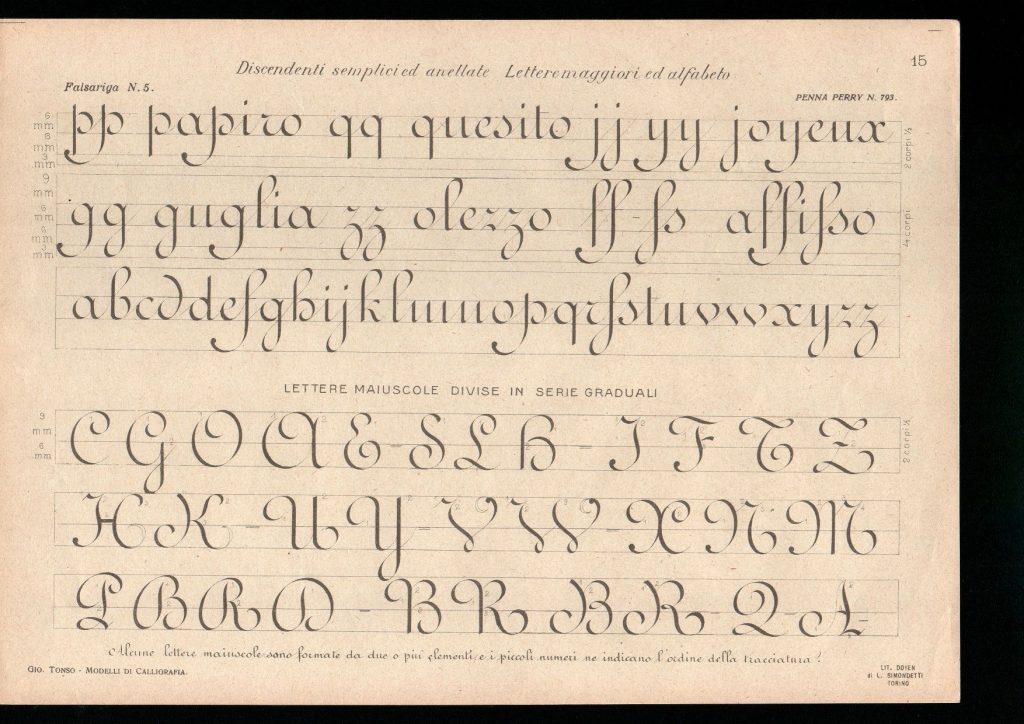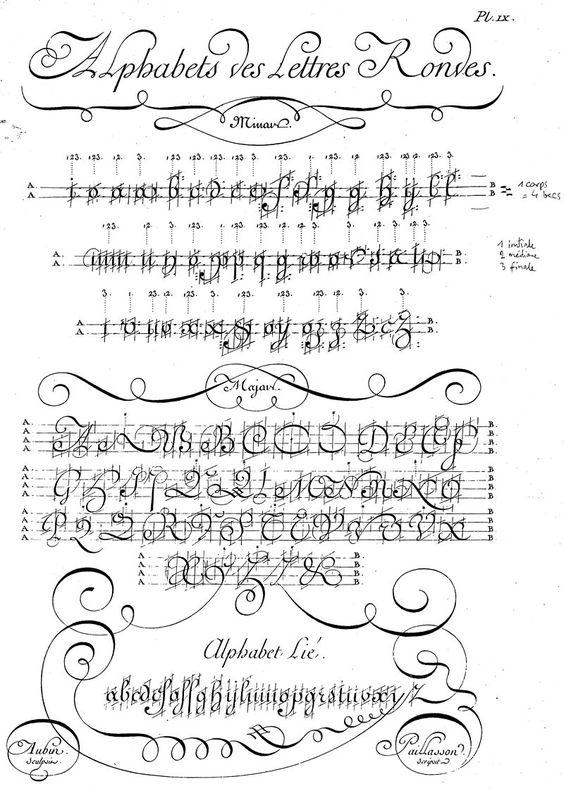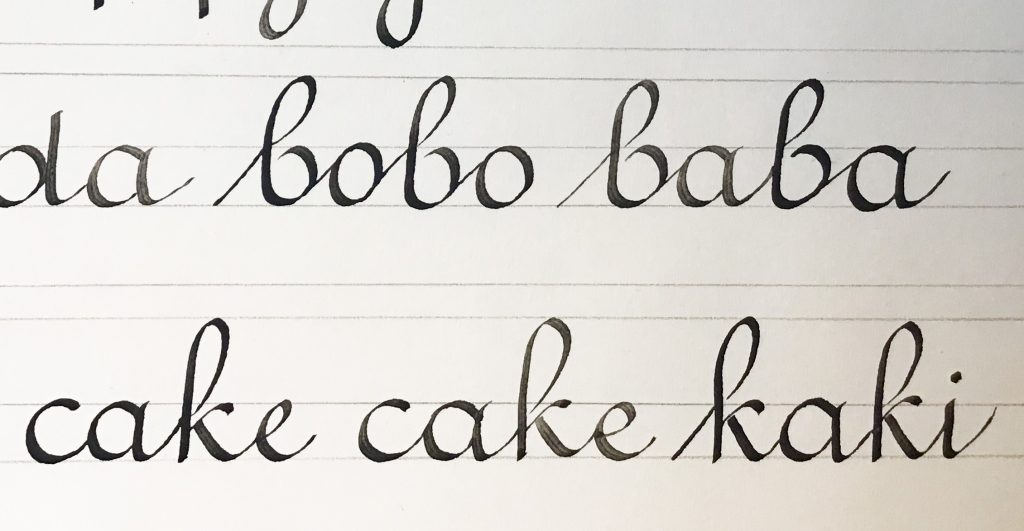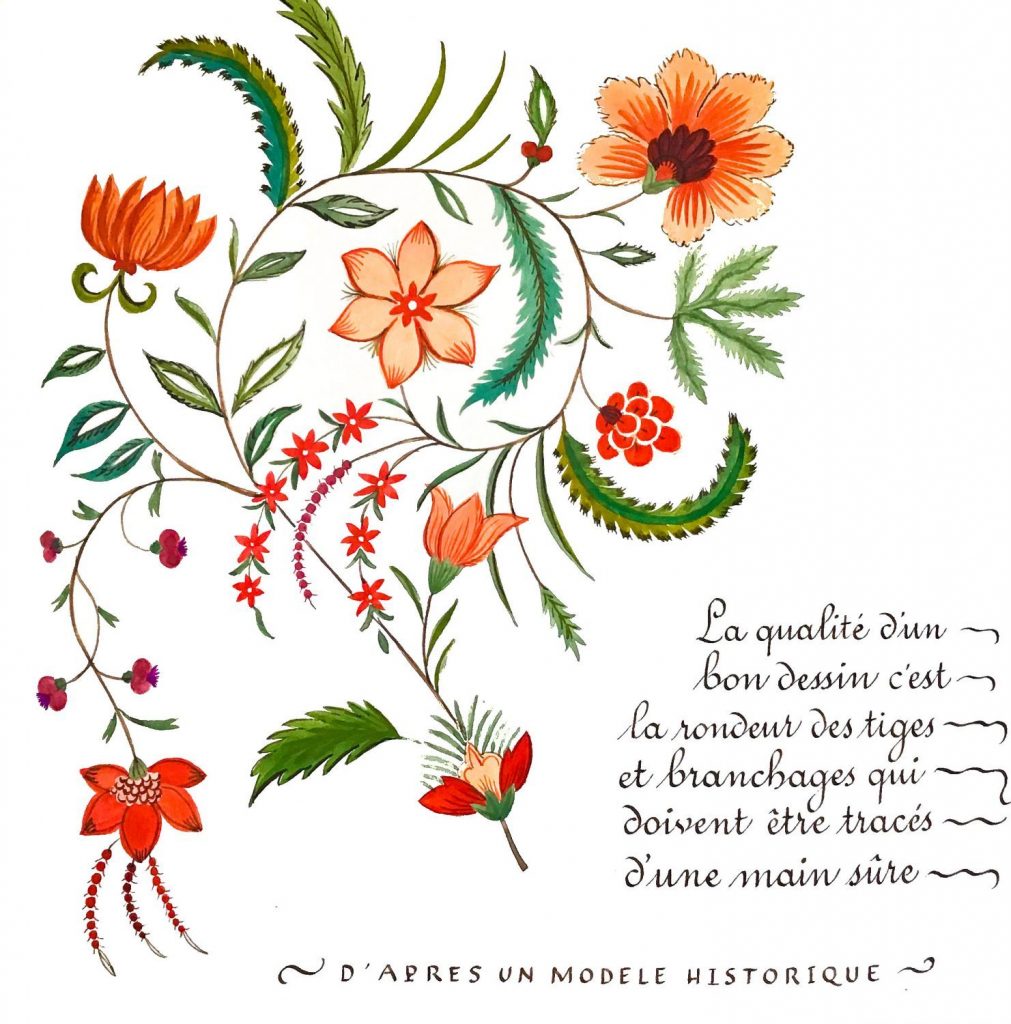
Ces dernières semaines j’ai été propulsée dans le XVIIIème siècle : cela a commencé avec un magnifique cours en ligne sur Skillshare sur la réalisation des motifs des Toiles de Jouy. J’ai profité de cet engouement soudain pour les cotons imprimés du XVIII pour aller visiter le très beau musée de la Toile de Jouy (à Jouy-en-Josas), ce qui a prolongé mon immersion dans le siècle des Lumières et le début de l’ère industrielle. C’est passionnant, j’en reparlerai sans doute plus longuement, mais tout cela pour vous dire que ce voyage, comme un fil que l’on déroule, m’a également amenée à reprendre la plume après de longues semaines d’abstinence.
C’est en admirant les nombreux documents d’époque (lettres commerciales, patentes, bons de commande…) que j’ai eu envie de me replonger dans la Ronde.
La Ronde : une écriture née au XVIème siècle
L’écriture Ronde est née des cursives gothiques, qui ont par ailleurs donné la Chancelière. Cette écriture s’exécute à la plume biseautée, et est principalement utilisée dans les affaires. Une de ses formes initiales s’appelle d’ailleurs la Financière. Il y eu de nombreux maîtres français qui ont participé à la formalisation de cette écriture. Citons, parmi d’autres, Louis Barbedor ou Louis Senault.
Si l’aspect historique vous intéresse vous pouvez bien sûr vous référer aux livres de Claude Mediavilla (Calligraphie et Calligraphie française), qui offrent de très nombreux exemples d’époque.
L’apprentissage de la Ronde
La Ronde n’est pas une écriture difficile. Droite, régulière et… ronde (évidemment), elle est aisément accessible. Elle fut d’ailleurs très longtemps l’écriture d’apprentissage scolaire en France, avant d’être remplacée par l’Anglaise.
On trouve de nombreuses ressources sur internet pour apprendre la Ronde, comme le Recueil Méthodique des Principes d’Ecriture, ou ces très belles planches italiennes dont je me sers principalement.
Le point d’attention principal est le rythme de l’écriture, imposé par la petite liaison oblique entre les lettres qui doit être bien régulière, et la rondeur qui confère à l’écriture sa générosité et son équilibre.
J’ai l’impression qu’elle est peu pratiquée ou mise en avant par les calligraphes : peut-être car moins spectaculaire que l’Anglaise ou la Chancelière, et aussi car elle se prête peu (pas) aux variations et aux fantaisies. Néanmoins, personnellement, je la trouve élégante, féminine bien qu’enfantine, légère et agréable.
Pour le débutant, je pense qu’elle est assez vite gratifiante car peu difficile.
Là où ça se complique…
… c’est qu’elle apparaît rarement seule, du moins c’est ce que j’ai constaté dans les documents que j’ai pu voir. En effet, elle est souvent utilisée en titre et en sous-titre, avec des tailles différentes, mais rarement sur un texte complet.
Le texte sera en général rédigé avec une écriture plus « expédiée », comme la Batârde ou la Coulée.
Document photographié au Musée de la Toile de Jouy. La Ronde est accompagnée d’écritures cursives comme la Bâtarde ou la Coulée.
D’autre part, elle est souvent accompagnée d’arabesques parfois complexes, qui demandent une grande fluidité et une grande maîtrise du geste du calligraphe.
Mais si on s’en tient à la Ronde elle-même, rien de compliqué pour se lancer.
Planche de Ronde de Paillasson – XVIIIème siècle
Comment j’ai travaillé la Ronde
J’ai travaillé avec une plume Brause, que je trouve plus précise donc plus appropriée que la Speedball. Au niveaux des encres, j’ai opté pour de l’encre ferrique, ou de la gouache diluée.
Pour me remettre dans l’écriture j’ai travaillé sur un module assez grand (1cm pour le corps de la lettre), avec une plume de 2mm. Puis je suis passée sur un module plus petit avec une plume de 1mm.
Les majuscules peuvent être ombrées avec de fines hachures
Ci-dessous, quelques exemples d’utilisation de la Ronde pour titrer, dans mes carnets :
Page de Garde de mon nouveau Carnet